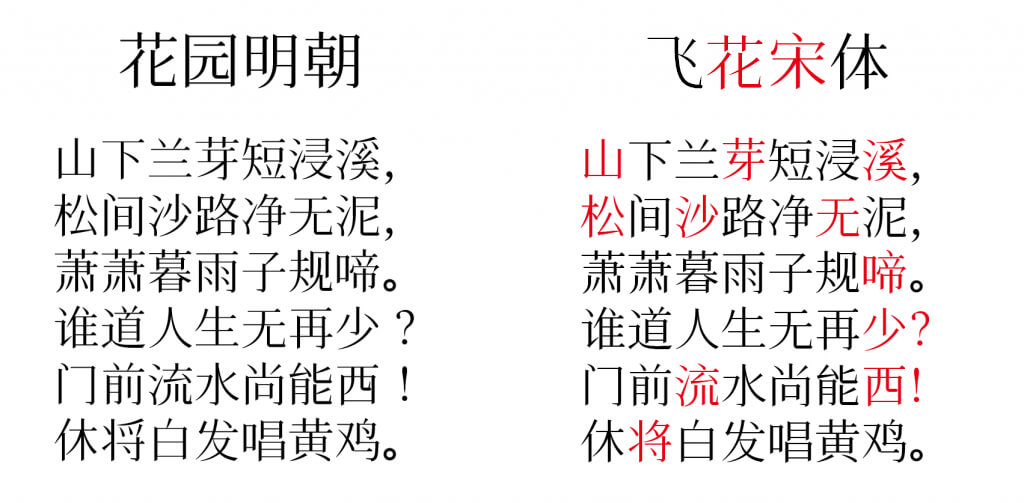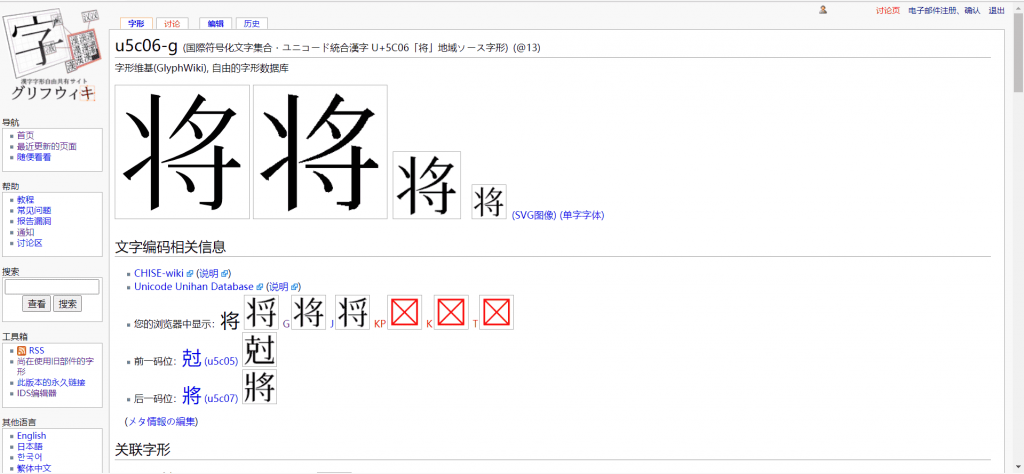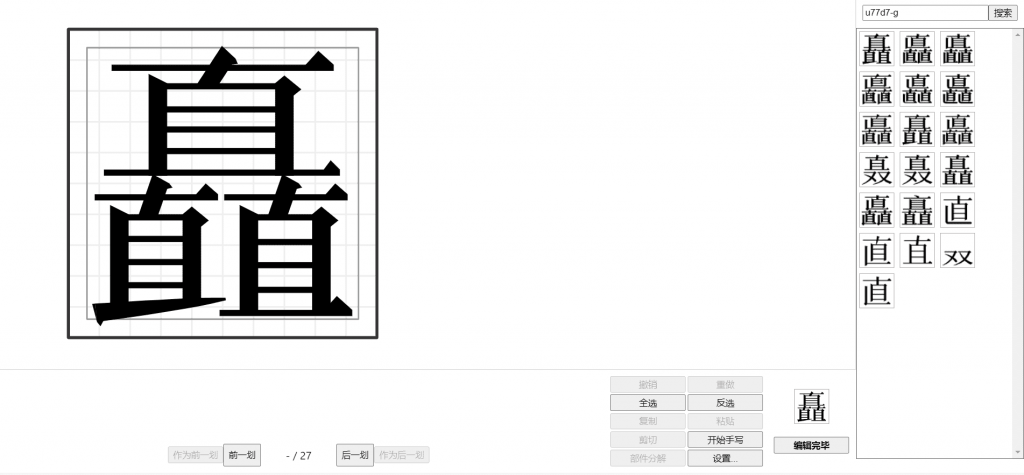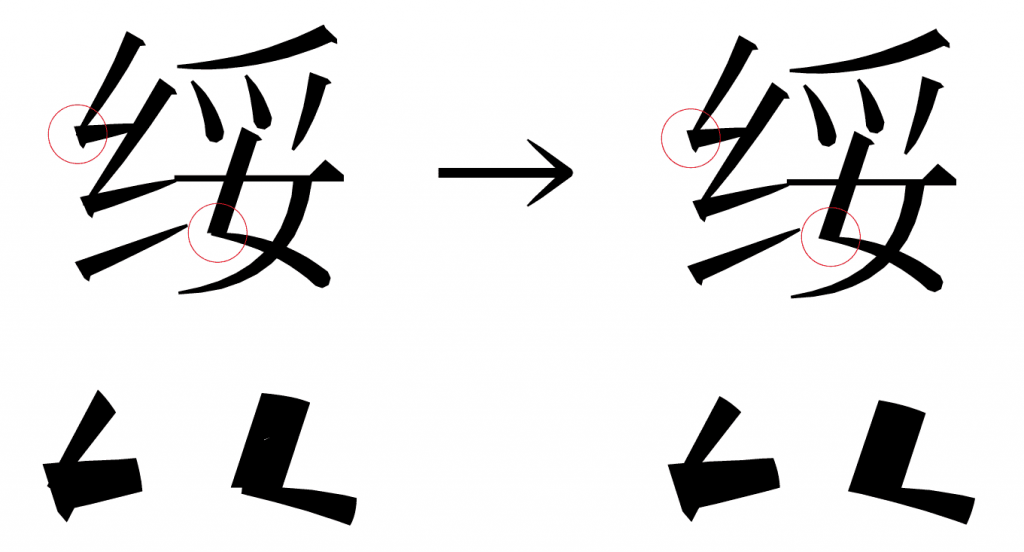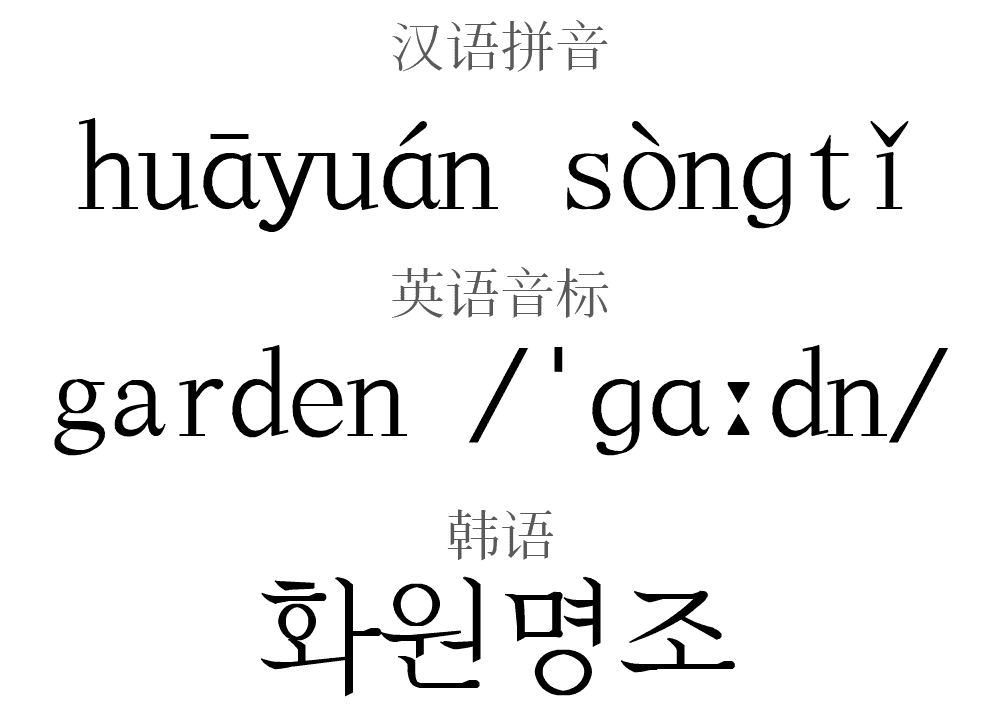
花园明朝 (Hanazono) 是一款免费字体,为GlyphWiki(字形wiki)所开发,几乎收录了所有汉字字形。缺点是字形以日本字形为准,有一些字不符合中文书写规范(不论是大陆规范还是港台规范)。在我了解到了字形wiki这个网站后,我决定将花园明朝体改成适合我们大陆人实用的版本。
起初,我只是单纯地将字形维基中的国标字形搬运过来,结构方面没有作改动,后来收到了大家的批评意见,才开始对这套字体用心制作。后来,经过多版的改造,《花园宋体》日渐地成熟。
《花园宋体》最初定的英文名是“HYSong”,后来发现与汉仪字库的英文名“HY×××”撞车,所以我决定将字体名称做改动。我保留了“花园”的“花”字,另起名为《飞花宋体》,英文名也改为“FlyFlowerSong”。
《飞花宋体》收录GB2312-80的6763个汉字、《通用规范汉字表》的8105个汉字、《现代汉语通用字表》的7000个汉字。此外按需增加一些较常用的表外汉字,包括古文里的字,同样只有简体。
其中,部分汉字的大陆字形并未制作,我也使用kage editor(HTML5)进行了创作。
在折笔处kage editor制作的效果不佳,对此进行更改,效果如下:
符号方面,目前将HKSCS、GB2312、Big5所收录的符号全部收录并作了修整,此外有选择地收录了日标和韩标的一些符号。
《飞花宋体》除了支持简体汉字之外,还支持俄语、希腊语、韩语、拉丁语、盲文以及中学阶段涉及的数学符号,未来如果有可能还会收录少数民族的语言文字。
本字体收录的其他字母符号如下: